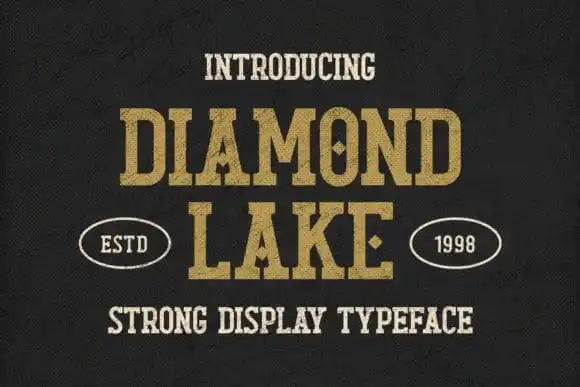
Diamond Lake Display Font – Download Grátis
A Diamond Lake Display Font é uma elegante escolha para quem busca uma aparência robusta e distintiva em projetos visuais. Com 99designs como seu criador, essa slab serif está revestida de uma impressão clássica e vintage que destaca-se imediatamente nas criações digitais. Perfeita tanto para revistas quanto para títulos, embalagens, marca, logotipo ou selos, a Diamond Lake é um recurso indispensável para designers buscando destacar suas ideias em ambientes de design moderno e tradicional. Seja você um entusiasta da criatividade em torno de revistas, jornais ou publicações digitais, ou um estilista atento às nuances das embalagens de produtos, a Diamond Lake Display Font é o complemento ideal para tornar suas criações ainda mais memoráveis e impactantes.